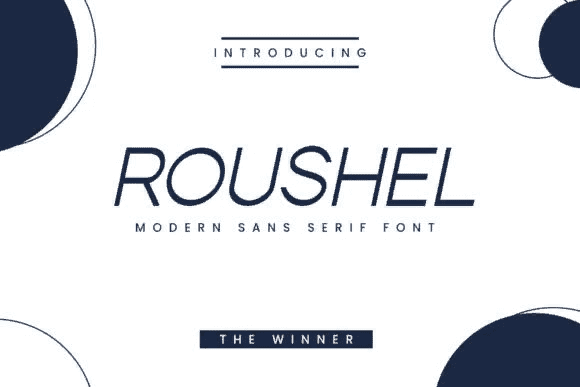
Название: Roushel Font (2021)
Roushel - это минимальный и аккуратный шрифт sans serif.
Его можно легко подобрать к невероятно большому набору проектов, поэтому добавьте его к своим творческим идеям и обратите внимание, как он их выделяет!